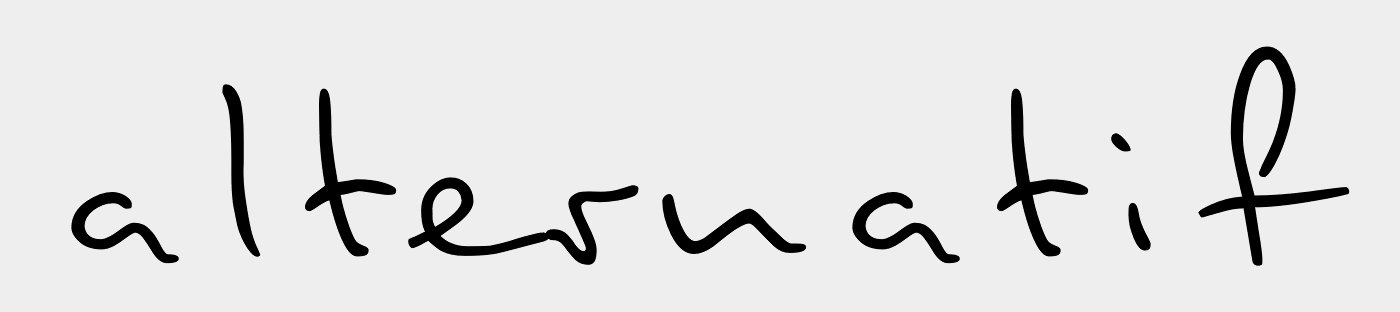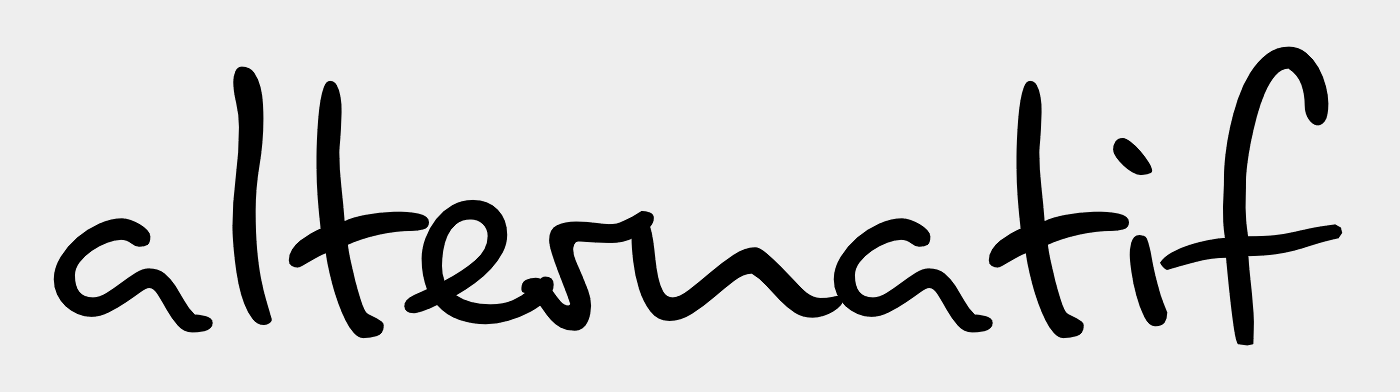
Schrift ähnlich PT Fog Script
ich habe letztens eine Einladung gesehen, auf der eine Schrift verwendet wurde, die der PT Fog Script sehr sehr ähnlich war.
r, m alles identisch. Allerdings sah das f anders aus, als bei der Fog Script (keine geschlossene Schleife).
Ich bin auf der Suche nach dieser Schrift (leider kann ich die Einladung nicht mehr zeigen - die wurde bereits entsorgt ... :-( )
Kennt jemand PT Fog Script Alternativen, die dieser sehr änlich sehen?